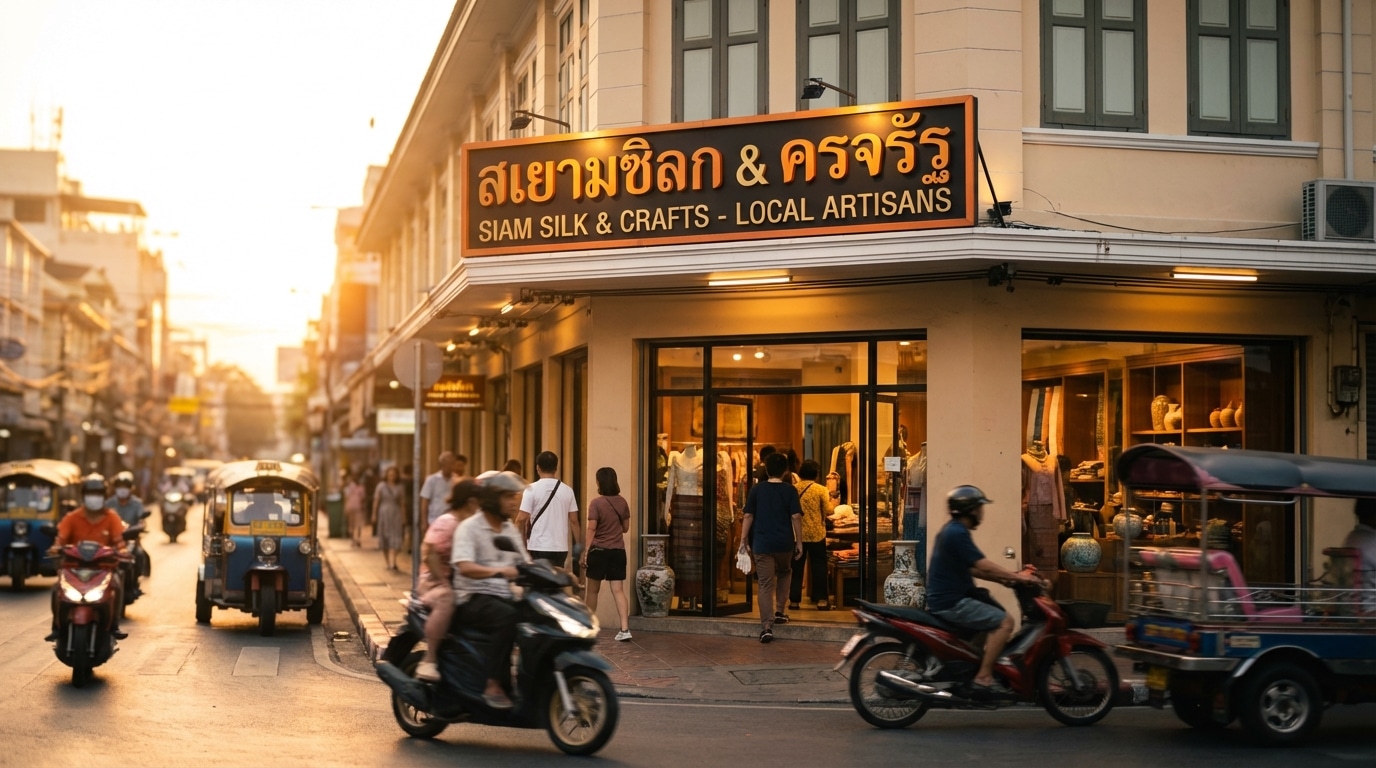
เทคนิคเลือกขนาดฟอนต์ป้ายโฆษณา ดึงดูดลูกค้าตั้งแต่ปากซอย
การทำป้ายโฆษณาให้โดดเด่นและสื่อสารได้อย่างมีประสิทธิภาพนั้นมีองค์ประกอบหลายอย่าง แต่หนึ่งในปัจจัยที่สำคัญที่สุดและมักถูกมองข้ามคือขนาดของตัวอักษร การเลือกขนาดที่ไม่เหมาะสมอาจทำให้ข้อความที่ต้องการสื่อสารถูกละเลยไปอย่างน่าเสียดาย โดยเฉพาะกับป้ายที่ติดตั้งในบริเวณที่มีการสัญจรอย่างรวดเร็ว
- ขนาดตัวอักษรมีความสัมพันธ์โดยตรงกับระยะการมองเห็น กฎพื้นฐานคือความสูงของตัวอักษร 1 นิ้ว สามารถอ่านได้ชัดเจนจากระยะ 10 ฟุต
- การเลือกใช้ฟอนต์ประเภท Sans Serif (ไม่มีเชิง) ช่วยเพิ่มความสามารถในการอ่านได้จากระยะไกล โดยเฉพาะเมื่อเทียบกับฟอนต์ที่มีความซับซ้อนหรือเป็นลายมือ
- ความคมชัด (Contrast) ระหว่างสีตัวอักษรและสีพื้นหลังเป็นปัจจัยสำคัญที่ช่วยให้ข้อความโดดเด่นและอ่านง่าย แม้ในสภาพแสงน้อยหรือมองจากระยะไกล
- การสร้างลำดับชั้นของข้อมูลโดยใช้ขนาดฟอนต์ที่แตกต่างกันสำหรับหัวข้อหลัก หัวข้อรอง และเนื้อหา ช่วยนำทางสายตาของผู้ชมและทำให้เข้าใจสาระสำคัญได้ในเวลาอันสั้น
- การทดสอบการมองเห็นป้ายจากระยะจริงก่อนการผลิตเป็นขั้นตอนที่จำเป็น เพื่อให้แน่ใจว่าขนาดและรูปแบบที่เลือกนั้นใช้งานได้ผลจริงในสภาพแวดล้อมนั้นๆ
บทความนี้จะเจาะลึกถึง เทคนิคเลือกขนาดฟอนต์ป้ายโฆษณา ดึงดูดลูกค้าตั้งแต่ปากซอย ซึ่งเป็นหัวใจสำคัญในการทำให้ธุรกิจขนาดกลางและขนาดย่อม (SME) สามารถแข่งขันและสร้างการรับรู้ได้อย่างมีประสิทธิภาพ การเลือกขนาดตัวอักษรที่ถูกต้องบนป้ายไวนิลหรือป้ายหน้าร้านไม่ได้เป็นเพียงเรื่องของความสวยงาม แต่เป็นศาสตร์ที่ผสมผสานระหว่างการออกแบบและการคำนวณทางกายภาพเพื่อให้แน่ใจว่ากลุ่มเป้าหมายสามารถรับข้อมูลได้อย่างครบถ้วนและรวดเร็วที่สุดแม้ในขณะเคลื่อนที่
ความสำคัญของขนาดตัวอักษรบนป้ายโฆษณา
ในโลกของการตลาดที่มีการแข่งขันสูง ป้ายโฆษณาเปรียบเสมือนด่านแรกที่สร้างความประทับใจและสื่อสารกับลูกค้าเป้าหมาย โดยเฉพาะสำหรับธุรกิจ SME ที่มีหน้าร้าน การทำป้ายโฆษณาให้สามารถดึงดูดความสนใจได้ภายในเวลาไม่กี่วินาทีถือเป็นความท้าทายอย่างยิ่ง ผู้คนที่เดินหรือขับรถผ่านมีเวลาเพียงชั่วครู่ในการมองและประมวลผลข้อมูล ดังนั้น ขนาดตัวอักษรบนป้ายจึงไม่ใช่แค่รายละเอียดเล็กน้อย แต่เป็นองค์ประกอบเชิงกลยุทธ์ที่ตัดสินว่าข้อความทางการตลาดนั้นจะไปถึงผู้รับสารหรือไม่
ขนาดตัวอักษรที่เล็กเกินไปจะทำให้ป้ายนั้นไร้ประโยชน์ เพราะไม่มีใครสามารถอ่านข้อความได้ทัน ในทางกลับกัน ขนาดที่ใหญ่เกินไปโดยไม่คำนึงถึงสัดส่วนและความสวยงาม ก็อาจทำให้ป้ายดูไม่เป็นมืออาชีพและรกสายตา การเลือกขนาดที่เหมาะสมจึงเป็นการสร้างสมดุลระหว่างความสามารถในการอ่าน (Readability) และความสวยงาม (Aesthetics) เพื่อให้ป้ายนั้นทำหน้าที่ของมันได้อย่างสมบูรณ์ คือการสื่อสารข้อมูลสำคัญ เช่น ชื่อร้าน โปรโมชั่น หรือจุดเด่นของสินค้า ได้อย่างชัดเจนและรวดเร็วที่สุด
หลักการพื้นฐานในการกำหนดขนาดฟอนต์
การกำหนดขนาดฟอนต์สำหรับป้ายโฆษณาไม่ได้อาศัยเพียงความรู้สึก แต่มีหลักการคำนวณที่อิงจากระยะการมองเห็นและสภาพแวดล้อม เพื่อให้ได้ผลลัพธ์ที่มีประสิทธิภาพสูงสุด การทำความเข้าใจหลักการเหล่านี้จะช่วยให้ผู้ประกอบการสามารถตัดสินใจเลือกขนาดตัวอักษรป้ายร้านได้อย่างมีหลักเกณฑ์
กฎมาตรฐานระยะการมองเห็น: 10 ฟุตต่อ 1 นิ้ว
หลักการที่เป็นที่ยอมรับในวงการออกแบบป้ายคือ “กฎ 10 ฟุตต่อ 1 นิ้ว” ซึ่งหมายความว่า ตัวอักษรที่มีความสูง 1 นิ้ว (ประมาณ 2.54 เซนติเมตร) จะสามารถอ่านได้อย่างชัดเจนจากระยะห่าง 10 ฟุต (ประมาณ 3 เมตร) กฎนี้เป็นจุดเริ่มต้นที่ดีในการคำนวณขนาดตัวอักษรเบื้องต้น
ตัวอย่างเช่น หากต้องการให้คนขับรถที่อยู่ห่างจากร้าน 100 ฟุต (ประมาณ 30 เมตร) สามารถอ่านชื่อร้านได้ชัดเจน ขนาดความสูงของตัวอักษรควรมีอย่างน้อย 10 นิ้ว (100 ฟุต / 10 ฟุตต่อ 1 นิ้ว) หรือประมาณ 25.4 เซนติเมตร การใช้สูตรนี้ช่วยให้สามารถประเมินขนาดที่ต้องการได้อย่างรวดเร็วและแม่นยำ
การคำนวณสำหรับสถานที่ติดตั้งที่แตกต่างกัน
สภาพแวดล้อมและตำแหน่งที่ติดตั้งป้ายมีผลอย่างมากต่อการกำหนดขนาดฟอนต์
- ป้ายหน้าร้านหรือปากซอย: สำหรับป้ายที่อยู่ใกล้กับทางเท้าหรือถนนในซอย ซึ่งผู้คนเดินหรือขับรถด้วยความเร็วต่ำ ระยะการมองเห็นอาจอยู่ที่ประมาณ 10-20 เมตร (ประมาณ 33-66 ฟุต) ในกรณีนี้ ขนาดตัวอักษรควรมีความสูงอย่างน้อย 3.3-6.6 นิ้ว (ประมาณ 8-17 เซนติเมตร) เพื่อให้มองเห็นได้ชัดเจนและดึงดูดความสนใจได้ทันที
- ป้ายริมถนนใหญ่หรือทางด่วน: สำหรับป้ายที่ติดตั้งริมถนนที่มีการจราจรหนาแน่นและรถยนต์ใช้ความเร็วสูง ระยะการมองเห็นจะไกลขึ้นและเวลาในการมองจะสั้นลงอย่างมาก ดังนั้น ขนาดตัวอักษรต้องใหญ่เป็นพิเศษ อาจต้องมีความสูงหลายสิบเซนติเมตรหรือเป็นเมตร ขึ้นอยู่กับระยะที่ต้องการให้มองเห็น
นอกเหนือจากระยะทางแล้ว ควรพิจารณาปัจจัยแวดล้อมอื่นๆ เช่น สิ่งกีดขวาง ป้ายของร้านค้าข้างเคียง หรือความสว่างของพื้นที่ เพื่อปรับขนาดให้เหมาะสมและโดดเด่นที่สุดในบริบทนั้นๆ
เทคนิคการออกแบบตัวอักษรเพื่อสร้างผลกระทบสูงสุด
นอกจากการเลือกขนาดที่ถูกต้องแล้ว การออกแบบองค์ประกอบอื่นๆ ของตัวอักษรก็มีความสำคัญไม่แพ้กัน เพื่อให้ป้ายโฆษณาสามารถสื่อสารได้อย่างมีประสิทธิภาพและสร้างความน่าจดจำให้กับแบรนด์
การเลือกประเภทฟอนต์: Sans Serif เพื่อความชัดเจน
ประเภทของฟอนต์มีผลโดยตรงต่อความง่ายในการอ่าน (Legibility) โดยทั่วไปแล้ว สำหรับป้ายโฆษณาที่ต้องการความชัดเจนจากระยะไกล ควรเลือกใช้ฟอนต์ในกลุ่ม Sans Serif (ฟอนต์ไม่มีเชิง) เช่น Helvetica, Arial, หรือ Futura เนื่องจากมีลักษณะที่เรียบง่าย ไม่มีส่วนตกแต่งที่ปลายตัวอักษร ทำให้สายตาสามารถจดจำและอ่านได้อย่างรวดเร็ว
ควรหลีกเลี่ยงฟอนต์ที่มีความซับซ้อน เช่น ฟอนต์ลายมือ (Script) หรือฟอนต์ที่มีรายละเอียดเยอะ (Serif) สำหรับข้อความหลักที่ต้องการให้อ่านได้เร็ว แม้ว่าฟอนต์เหล่านี้อาจจะสวยงามและสื่อถึงบุคลิกของแบรนด์ได้ดี แต่ก็อาจลดทอนความสามารถในการอ่านเมื่อมองจากระยะไกลหรือในเวลาสั้นๆ ควรให้ความสำคัญกับความชัดเจนเป็นอันดับแรกเสมอ